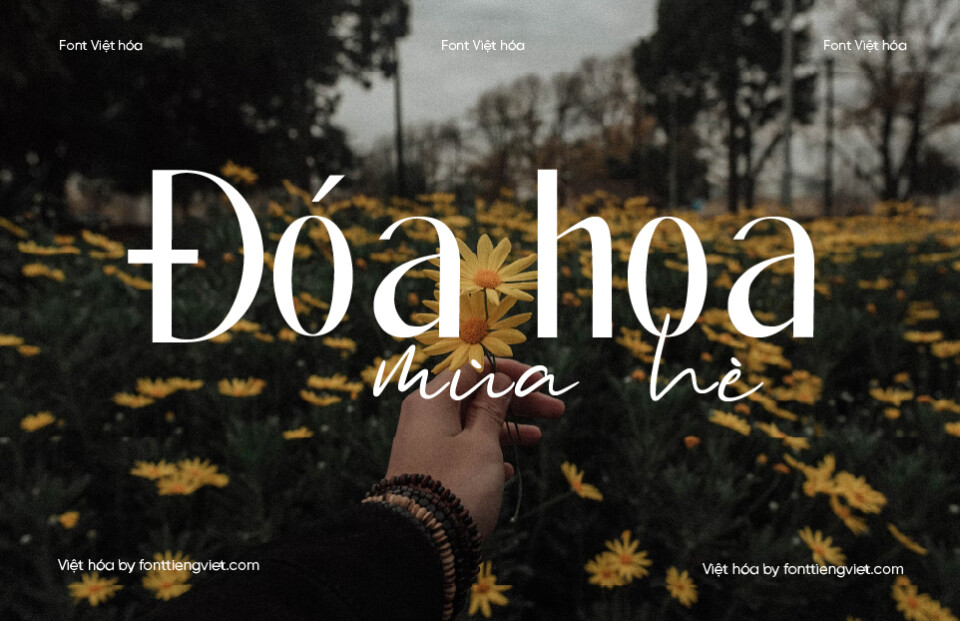
Font Việt hóa 1FTV VIP Slogest
Giới thiệu về Font Việt hóa 1FTV VIP Slogest
Trong thế giới đồ họa hiện đại, việc lựa chọn một bộ Font Miễn Phí chất lượng luôn là ưu tiên hàng đầu của các nhà thiết kế. Đặc biệt, Font Việt hóa 1FTV VIP Slogest nổi lên như một hiện tượng nhờ sự kết hợp hoàn mỹ giữa nét cổ điển và hơi thở đương đại. Đây là bộ font được tinh chỉnh kỹ lưỡng về dấu tiếng Việt, giúp khắc phục hoàn toàn lỗi hiển thị phổ biến trên các phần mềm thiết kế như Photoshop hay Canva. Với cấu trúc chữ thanh thoát và các đường nét uốn lượn tinh tế, Slogest mang đến một diện mạo hoàn toàn mới, đầy chuyên nghiệp cho mọi dự án truyền thông từ học đường đến doanh nghiệp.
Đặc điểm nổi bật của Font Việt hóa 1FTV VIP Slogest
Phong cách thiết kế sang trọng và hiện đại
Font Việt hóa 1FTV VIP Slogest sở hữu phong cách Serif (có chân) cách tân, tạo cảm giác tin cậy và vững chãi. Điểm nhấn của bộ font này nằm ở các nét nối giữa các ký tự được xử lý mượt mà, tạo nên một dòng chảy thị giác tự nhiên. Đối với các bạn học sinh, sinh viên đang tìm kiếm sự khác biệt cho các bài thuyết trình hay báo cáo thực tập, Slogest chính là lựa chọn giúp nâng tầm giá trị nội dung một cách hiệu quả nhất.
Khả năng tương thích và tối ưu hóa tiếng Việt
Một trong những lý do khiến Font Việt hóa 1FTV VIP Slogest được ưa chuộng chính là hệ thống dấu câu được đặt ở vị trí chuẩn xác, không bị đè hay lệch so với mặt chữ chính. Điều này cực kỳ quan trọng trong thiết kế in ấn tại Việt Nam, nơi mà các quy chuẩn về ngôn ngữ luôn được đặt lên hàng đầu. Bộ font này hỗ trợ đầy đủ các ký tự đặc biệt, đảm bảo văn bản của bạn luôn rõ ràng và dễ đọc trên cả thiết bị di động lẫn màn hình máy tính.
Ứng dụng thực tế của bộ font trong đời sống
Thiết kế thương hiệu và truyền thông
Nhờ vẻ ngoài lịch lãm, Font Việt hóa 1FTV VIP Slogest thường xuyên được sử dụng trong việc thiết kế logo, bộ nhận diện thương hiệu cho các cửa hàng thời trang hoặc quán cà phê phong cách vintage. Sự kết hợp giữa nét chữ nghệ thuật và tính ứng dụng cao giúp các designer dễ dàng tạo ra những ấn phẩm ấn tượng mà không tốn quá nhiều thời gian chỉnh sửa thủ công.
Sử dụng trong giáo dục và văn phòng
Trong môi trường giáo dục, việc sử dụng các mẫu chữ đẹp như Font Việt hóa 1FTV VIP Slogest giúp các tài liệu giảng dạy trở nên sinh động và thu hút sự chú ý của học sinh hơn. Các thầy cô giáo có thể ứng dụng font chữ này để làm tiêu đề cho các slide bài giảng hoặc thiết kế bằng khen, giấy chứng nhận cuối năm. Sự trang trọng của Slogest sẽ làm cho các món quà tinh thần trở nên ý nghĩa và chuyên nghiệp hơn bao giờ hết.
Kết luận về bộ Font Việt hóa 1FTV VIP Slogest